【明報專訊】「思緒俠」這個名字,你也許會覺得陌生;但一打開他的IG專頁,看到各種時歪時正的電腦或手寫繁體字,配上各式各樣風景圖,你便大概再難以忘記他把每個繁體字重新塑造形象的「畫風」。思緒俠真身Roy Chan,出身廣告系,原本與造字毫無關係,但他在不同公司當設計師時,發現中文設計字體數量少,常要借用日文字體,因而偶爾面對缺字的問題,機緣巧合下便開始造字。2019年適逢轉工,嘗試在專頁分享字形加以修飾的詞語或短句,在網絡吸引不少目光,結果乾脆全職「瞓身」造字。
成立思緒俠造字後,Roy借字體設計推出不少產品,如印滿歌詞的電話殼、4色開瓶器、繁體字萬字夾等,出乎意料大受歡迎。當中不得不提的是以香港為主題的月曆系列,本身熱愛創作系列作品的他自言,「月曆才稱得上首個大型企劃,以香港為主題是因為我相信設計之目的是改善生活。我和很多香港人一樣,同樣生活在一個壓迫、速度快、一定要努力的城市。但為何一定是這樣?基於這些感受和觀察,我想做一個項目,像跟朋友傾偈,想告訴大家香港有什麼好和不好,我都明白」。
曾因工作迷失 轉化成設計靈感
2020年首個推出的月曆名為「生於香港的無奈」,每個月份都以一句總結,一年共有12句文案,譬如3月主題「香港——令我瘋狂地做大家認為正常的事」,便取自Roy的自身經歷。他苦笑道:「我以前經常轉工,很簡單想加人工和升職,逐漸轉工到達一個階段連自己都害怕。究竟轉工為了什麼?我會不經意給自己壓力,想在最短時間上到最高位置,完全處於雙眼被蒙蔽(盲目)的狀態。」現在回想,他仍然覺得以前忙得太不尋常,卻不曾意識為何有這種「動力」,也許正是受到香港文化影響,令他誤以為人生只得一條「康莊大道」。迷失以後,他選擇慢下來還原基本步,重投創作,而創作亦燃起他的設計慾,「我想做一些大家都會記得的事」。
今年,他延續月曆企劃,推出「守在離岸的香港」月曆,每月句子依舊一矢中的,在讀者腦海縈繞。根據Google資料,自2019年6月起,香港有關移民資訊的搜尋度急升,2020年當政府拘捕黎智英、李卓人等後,搜尋度再度上升,移民成為香港人近年最大的議題之一。於是Roy想到,不如寫6句有關香港和6句香港人憧憬的某處的句子,互相呼應,突顯香港人就「離岸」的內心糾結。例如1月的「這裡尚有太多不願作的道別」和2月「那裡填滿房子的是空間」,一正一負為香港人喊出心聲。「有人向我反映去年的主題太負面,但不得不承認的是,在香港生活本身就很負面,今次嘗試轉變呈現手法。」
在「不願作的道別」一句,他以輕柔的線條呈現藕斷絲連的感覺,「填滿房子」一句則大膽地以正方形框住文字(圖a),象徵房屋限制,卻帶點跳脫輕盈感,有創意之餘,最重要是每個字也用心配合主題和意境。當主流大眾總是以為設計要愈多畫面愈好,他反倒選擇在最小的空間創作。「我們並不是賣字體,或手機殼等產品,而是想帶出繁體字的可能,只憑一個字去說故事。」即使簡單如一個詞彙,從改變它們的筆畫、風格、方向等,便能予人截然不同的感覺。
造字體,每天面對的都是看似單調的字和筆畫,有何值得沉迷之處,促使他希望有朝一日造出一套全新的繁體字呢?他笑說:「悶㗎,造字過程只有白底黑字,灰色就是留白,沒有其他。但筆畫有多粗幼,留白留多少,找到樂趣是會上癮的。字體不是顏色、排版,只是在正負中間找到樂趣,正!」撇除造字,他仍不忘融入更多設計元素於月曆內。若細心留意,月曆卡上面一邊全是凹凸不平的曲線,原來暗藏玄機,只要把12張月曆卡拼湊在一起,便成了獅子山的圖案。
獅子山精神,近年一直被年輕一代視為屬於老一輩的精神,為何要將獅子山放進去?「想過用維港線或其他山脈線象徵,但都不合適。我們雖然口說摒棄,但想深一層,我們還是處於獅子山精神裏,香港人在過去數年如何群策群力,展現同路人的默契,其實仍然是一種獅子山精神。」有些字句,月頭時你未必領會,過了一個月翻看可能有另一番感受,月曆上的獅子山圖案亦然。在Roy眼中,因為有時間流逝才有成長和覺悟,慢慢地經歷各種事情後,自能看到一整年的進步,把獅子山合併成為一個完整的形態。
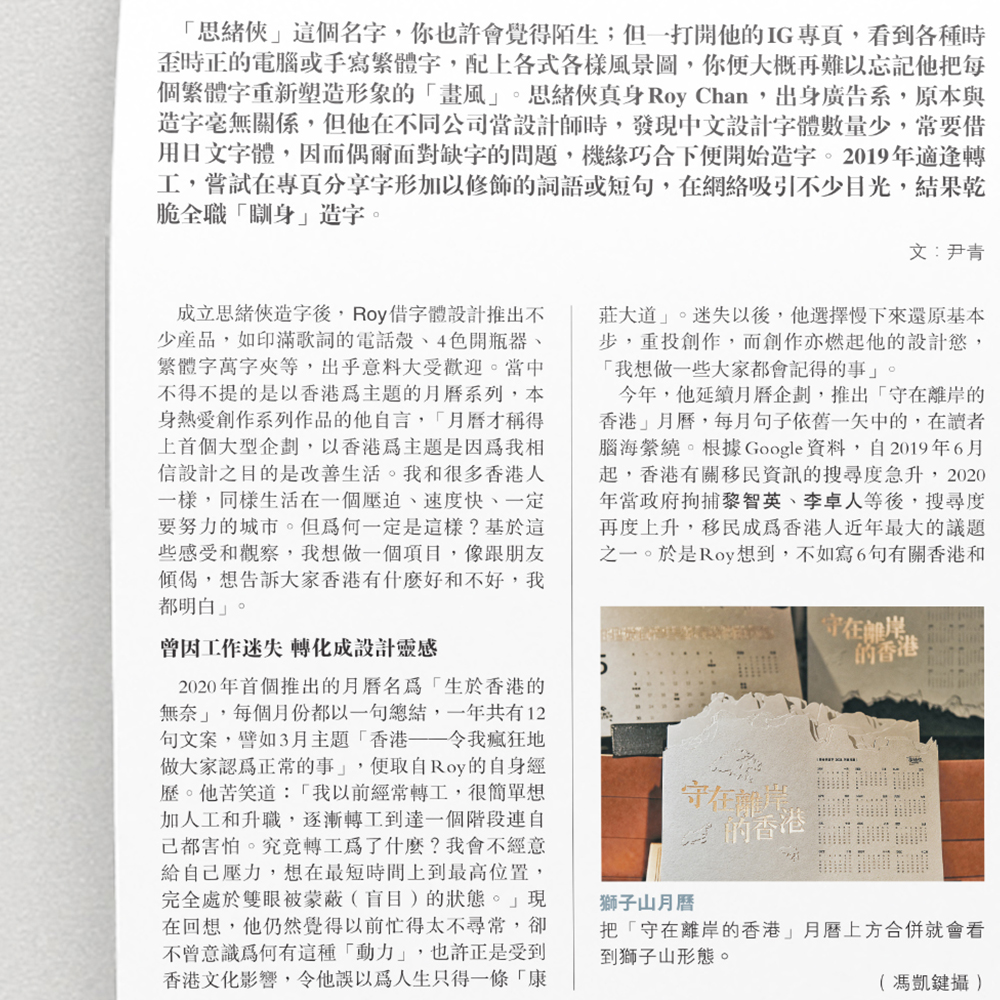
「不要只放大眼前限制」
自2019年,不少香港人陷入前所未有的失落,到2020年疫情一發不可收拾,他認為這時候我們更需要積極和正面。「在香港生活的確無力感很重。有些字今日已經不能說,但我們不要只放大眼前的限制,明明可以做的還有很多。一個字也可以玩得出神入化,盡做吧。」推出這個月曆時,他也抱着這樣的心態,卻意外獲得不少顧客認同,甚至在推出前已有不少人查詢,「有很多人臨離開香港前,專程問可否早點拿到月曆,可想而知離岸是每個香港人都在面對的切身問題」。但離岸前,他選擇「守」,不論以字為生,還是在香港,總有艱難想放棄的時候,但他以12月的句子作結。「這裡離了岸卻依舊是香港;那裡離了岸也可以是香港」,正是他堅持為香港人寫字造字,繼續把設計化作意念感動人心的原因。